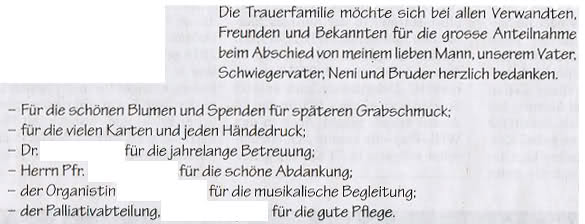
Das ist ja nicht nur graphisch, sondern auch grammatisch bemerkenswert.
Für mich als Bayer nicht. :-)am heißt hier auf dem, auf den und am.
Roberts wildes Schalenbild ist immerhin sinnrichtig, zumal da jemand ganz offensichtlich keine einzige Tasse mehr im Schrank hat. Ob da nun die Comicohne Schuld trifft oder nicht … ich hoffe mal, dass dann am Ferticschluss etwas mehr herausschaut, als bloß eine tektonische Todesanzeige.
Auch hier ist wieder nicht nur die Schriftwahl, sondern auch die Formulierung bemerkenswert. Warum verschickt man eine Absichtserklärung, sich bedanken zu wollen, statt sich einfach und tatsächlich zu bedanken?
… Absichtserklärung …
Ist möchte wirklich eine Absichtserklärung? Ich sehe es eher als Es ist uns wirklich eine Herzensangelegenheit, wir sagen es nicht nur so, sondern möchten es wirklich tun an.
Dann sollen sie es auch wirklich tun:
»Die Trauerfamilie bedankt sich bei allen ...«
Na, ihr Oh-Null-Experten, dann ordnet doch diese Zeichen mal richtig zu!
(Lösung erscheint nach einem Klick aufs Bild.)
der mann, schwiegervater, neni (? nanny ?) und bruder war sicher auch noch architekt.
grosse anteilnahme. argh.
Neni ist ein Synonym für Großätti, Ähne, Ehni, Ehnel … Gemeint ist der Großvater.
Naja, Herr RobertMichael, da diese «Danksagung» heute in einer Schweizer Zeitung vervielfältigt wurde, ist groß, wenn gross geschrieben steht. Und der Neni ist – wie Bertel schon richtigstellte – tatsächlich der Grossvater (Großvater). Oder romanisch auch Tat. Welchem Beruf der Verstorbene verloren ging, entzieht sich meiner Kenntnis. Vielleicht war er Schriftsetzer? Oder gar Geologe?
Aber vom Tod zurück ins pralle Leben: jedesmal wenn ich diese Tafel kreuze, frage ich mich, ob jetzt – vielleicht wegen dem hohen Goldpreis? – die Leute schon ihren Intimschmuck verkaufen?
ach ja die schweizer, wollen das ß ja nicht ;)
neni, war mir bisher aber echt noch nie untergekommen, danke. man lernt immer wieder dazu.
schreibt ihr in der schweiz dann auch ohringe anstelle von ohrringe?
Hier am Beispiel von wollen statt möchten erklärt, aber kommt ja auf das Gleiche raus:
Amüsant zu lesen! Indirekten Sprechakte ... beim Weg in die Kantine kein Problem, beim Gespärch zw. Flugkapitän und Co-Pilot war das schon oft tödlich – für alle an Bord.
Es gibt also Gründe und Situationen, es penibel mit der Sprache zu nehmen, aber eben alles zu seiner Zeit.
schreibt ihr in der schweiz dann auch ohringe anstelle von ohrringe?
Was glaubt er, warum ich – Schweizer – diese «Ohringe» wohl als Intimschmuck lese …
Aha. So ist das gemeint, dass der O-Ring ins Reich der Dichtung gehört, wie mir ein Sanitärinstallateur (Klempner) unlängst weismachte.
Ist ein Ohr-Ing. eigentlich ein HNO-Techniker?
Es gibt also Gründe und Situationen, es penibel mit der Sprache zu nehmen, aber eben alles zu seiner Zeit.
Ja, zum Beispiel, wenn man möchte, daß das, was man ins Netz stellt, auch von jemandem gelesen wird. Ich hab den Beitrag nach den ersten Sätzen weggeklickt, weil er in grauenhaftem Deutsch verfaßt und voller Fehler ist.
Ja, so was find ich auch total cool :-D Irgendjemand hat doch auch mal ein Parkhausleitsystem so realisiert ... :grübel:
Als Parkhausleitsystem finde ich es aber super, weil sinnvoll eingesetzt. Parkhäuser sind ja häufig ganz schön irreführend beschildert. In Südafrika hatte ich mich kürzlich schon fast damit angefreundet in einem zu leben, weil ich nicht mehr glaubte rauszufinden. ;-)
Als Parkhausleitsystem finde ich es aber super, weil sinnvoll eingesetzt.
Für mich fällt das eher unter Kunstwerk oder Werbegag. Es funktioniert doch nur von ganz wenigen einzelnen Sichtpunkten, die sich prima in den Fotos zeigen lassen, aber nicht der Realität der Benutzer eines solchen Systems entsprechen.
Na gut. Ich habe mich halt in SA über ein paar Schilder geärgert, die aus zwei Richtungen sichtbar waren und den Benutzer total irritiert und in die falsche Richtung geführt haben. Deshalb schien es mir sehr plausibel, eine Beschriftung einzurichten, die immer nur aus dem jeweils richtigen Blickwinkel den Weg weist. Aber »in echt« funktioniert das vermutlich wirklich nicht durchgängig. :-)